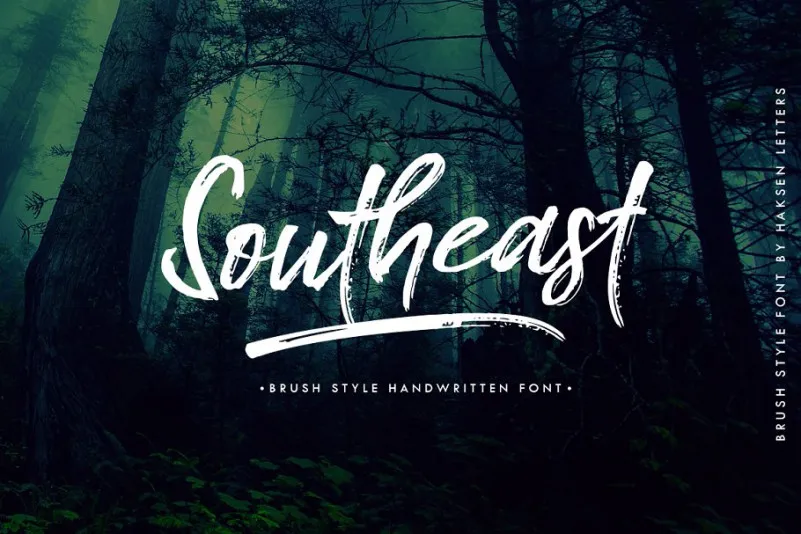
Southeast Brush Font – Download Grátis
Estou aqui a nova opção de fonte “Southeast Brush Font” para ajudar você a adicionar um toque especial aos seus designs gráficos, especialmente se está procurando por uma fonte que transmita autenticidade e criatividade. Este moderno estilo brush é perfeito para dar à sua arte digital uma sensação única de mão-durante, tornando-a mais autêntica e envolvente. O designer Hamilton introduziu essa nova fonte fresca e artesanal que se destaca na categoria dos tipos de script. A “Southeast Brush Font” é ideal para uma variedade de aplicativos gráficos como cartões de felicitações, materiais de marca, cards de negócios, citações, panfletos, entre outros. Com essa fonte, você poderá estabelecer um contato genuíno e personalizado com seus clientes, seja através de um cartão de visita ou de uma publicação em redes sociais. A sua escolha pode transformar simplesmente qualquer design em algo mais sofisticado e singular. É perfeito para todos os tipos de marcas – o que torna a “Southeast Brush Font” uma opção incrivelmente versátil para ajudá-lo a alcançar seus objetivos de design!